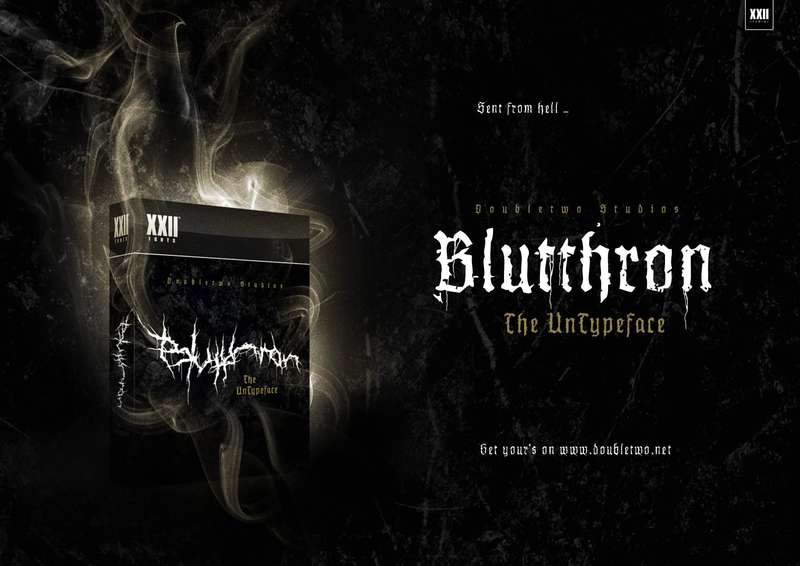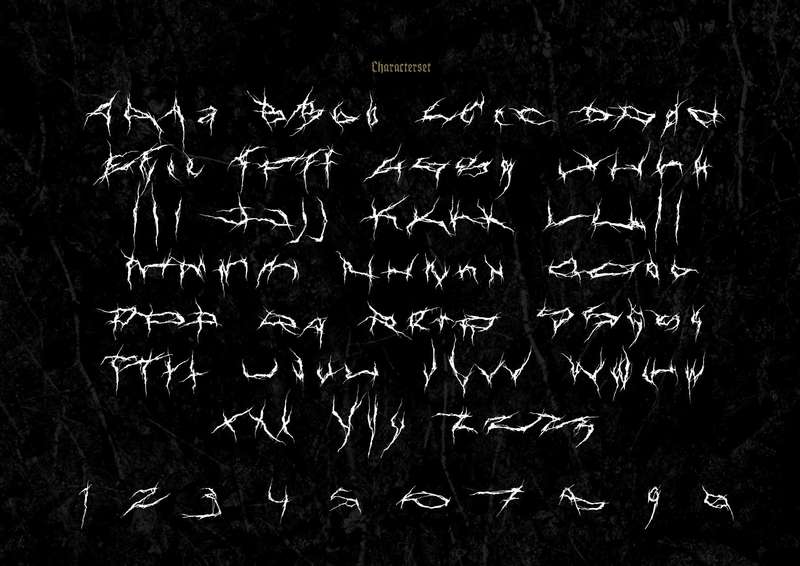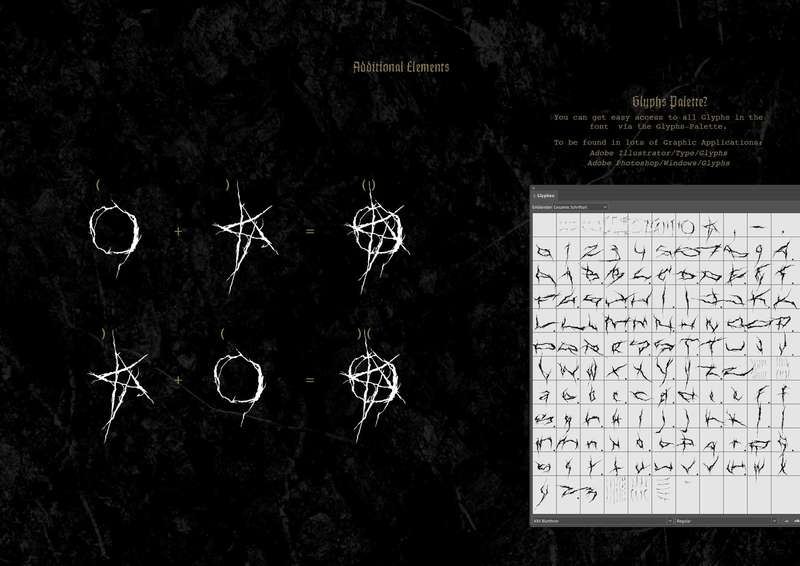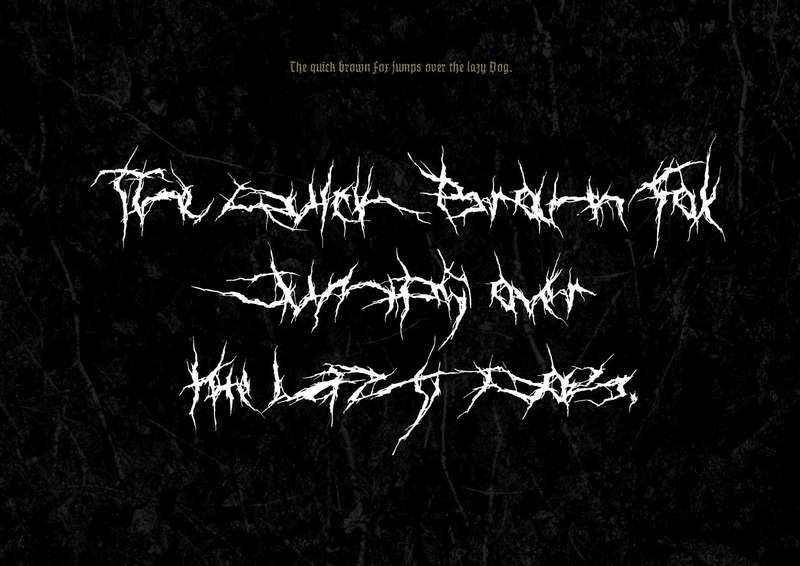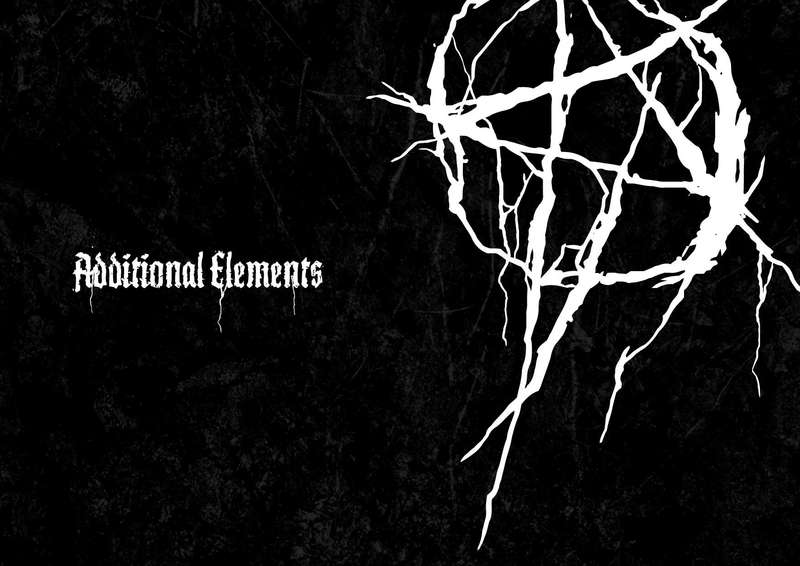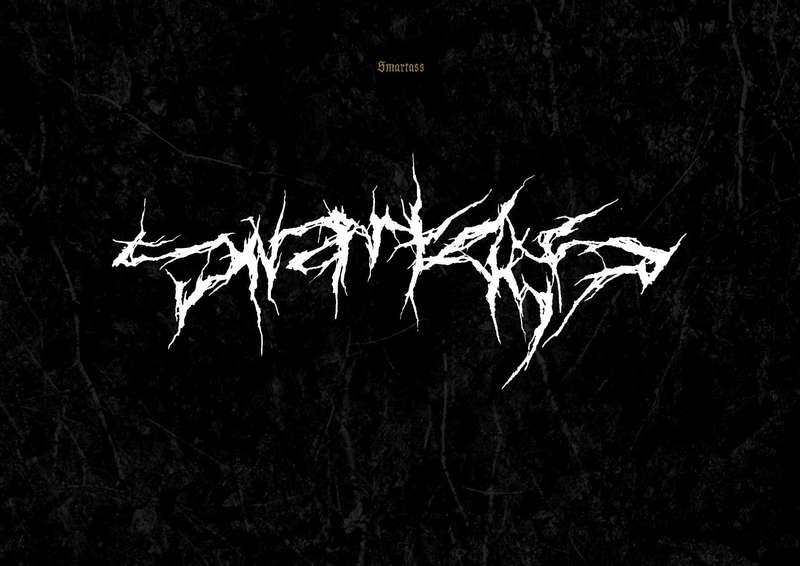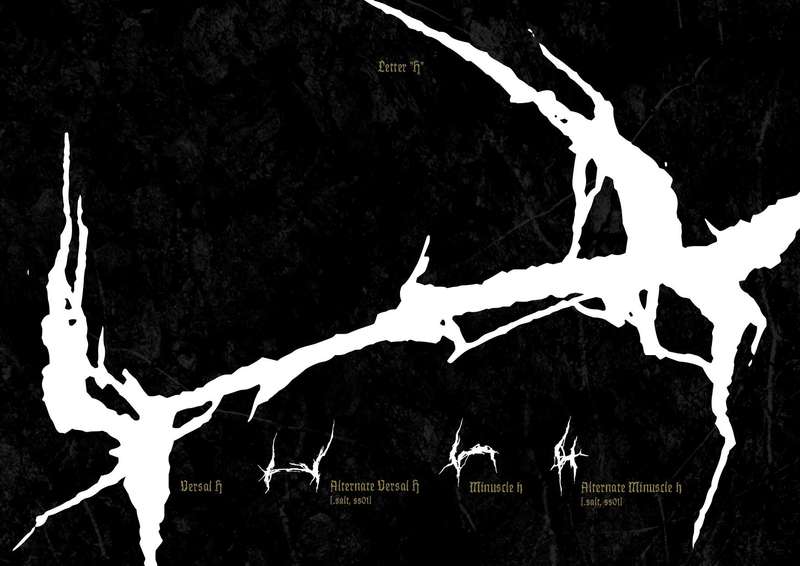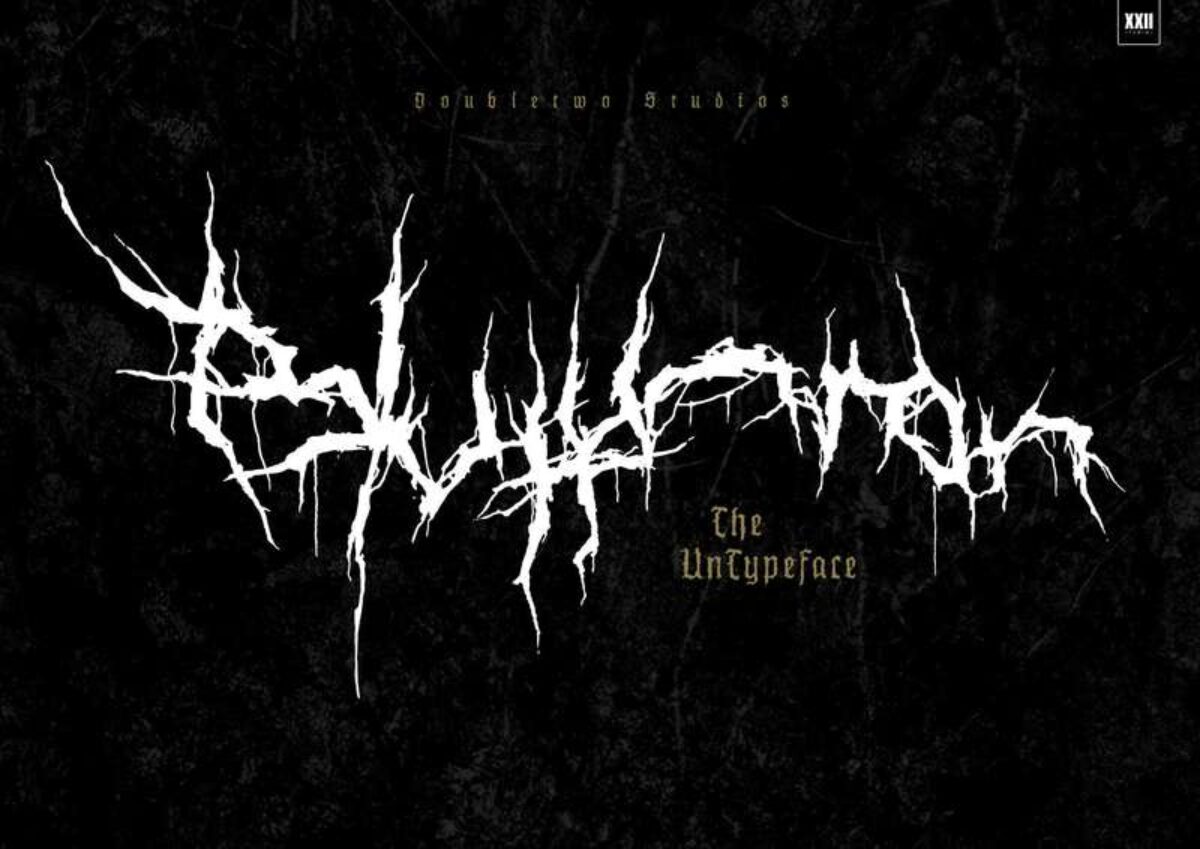
O lettering de black metal de XXII Blutthron do Doubletwo Studios
O lettering de black metal é um estilo distinto de tipografia comumente usado em gêneros musicais extremos, como death metal, black metal e grindcore. Esse estilo de letras é frequentemente caracterizado por seus recursos altamente ilegíveis, irregulares e ornamentados, tornando uma escolha ideal para capas de álbuns, pôsteres e outros elementos visuais que exigem uma estética sombria e suja.
O slogan que o pessoal do Doubletwo Studios resolveu usar para descrever a XXII Blutthron é simples: ilegibilidade máxima para seus projetos musicais mais sombrios. Esta fonte é uma fonte de logotipo extrema projetada para música extrema. Se você é apaixonado por death, black metal, grindcore ou o gênero de filmes de terror, pode gostar de usar essa fonte.
Um dos aspectos mais importantes desse tipo de lettering usado no visual de black metal é sua capacidade de transmitir uma sensação de caos e sobrenatural. As formas irregulares e angulares e as serifas nítidas das letras criam uma atmosfera misteriosa e quase perturbadora, perfeita para capturar o espírito da música extrema.
Além de seu estilo visual único, o lettering de black metal também é altamente personalizáveis, permitindo que designers gráficos e artistas experimentem diferentes formas, cores e texturas. Muitas fontes de black metal vêm com uma variedade de símbolos e pingos, que podem ser usados para criar composições intrincadas e visualmente impressionantes.
Apesar de sua estética altamente específica, o lettering de black metal encontrou um lugar em uma ampla gama de contextos criativos, desde pôsteres de filmes de terror até instalações de arte de vanguarda.